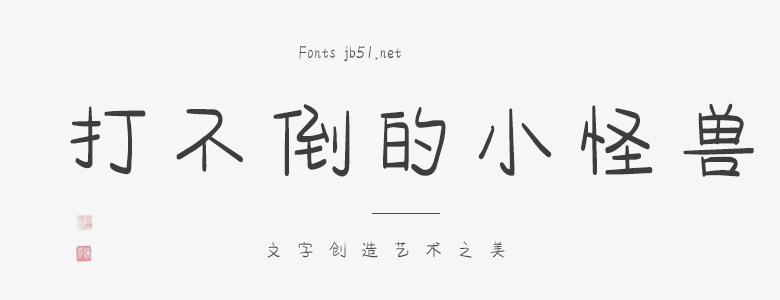
打不倒得小怪獸這是一款可商用創(chuàng)意體,簡(jiǎn)約的風(fēng)格,加上可愛(ài)的字體設(shè)計(jì),該字包含6763個(gè)中文、字母、符號(hào)和數(shù)字,適用于文藝及兒童類品牌廣告和產(chǎn)品包裝設(shè)計(jì),以及社交網(wǎng)絡(luò)的個(gè)性化用字